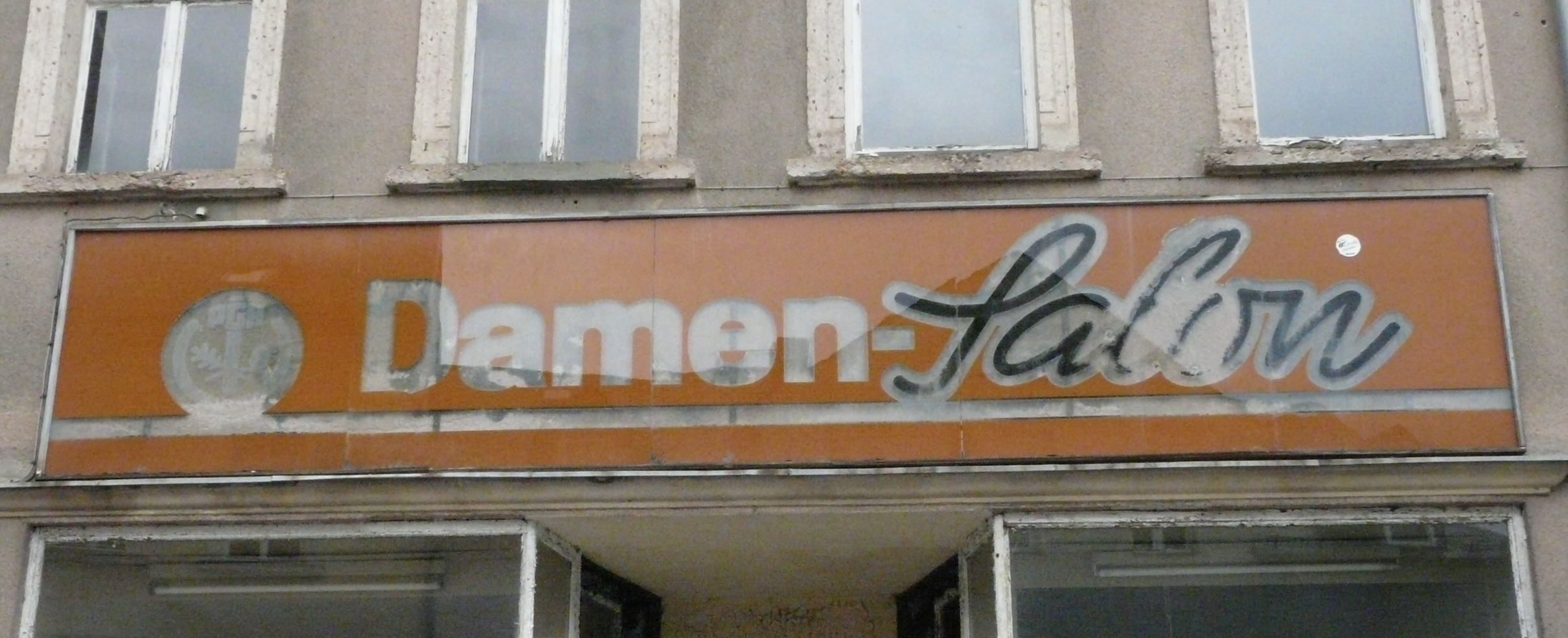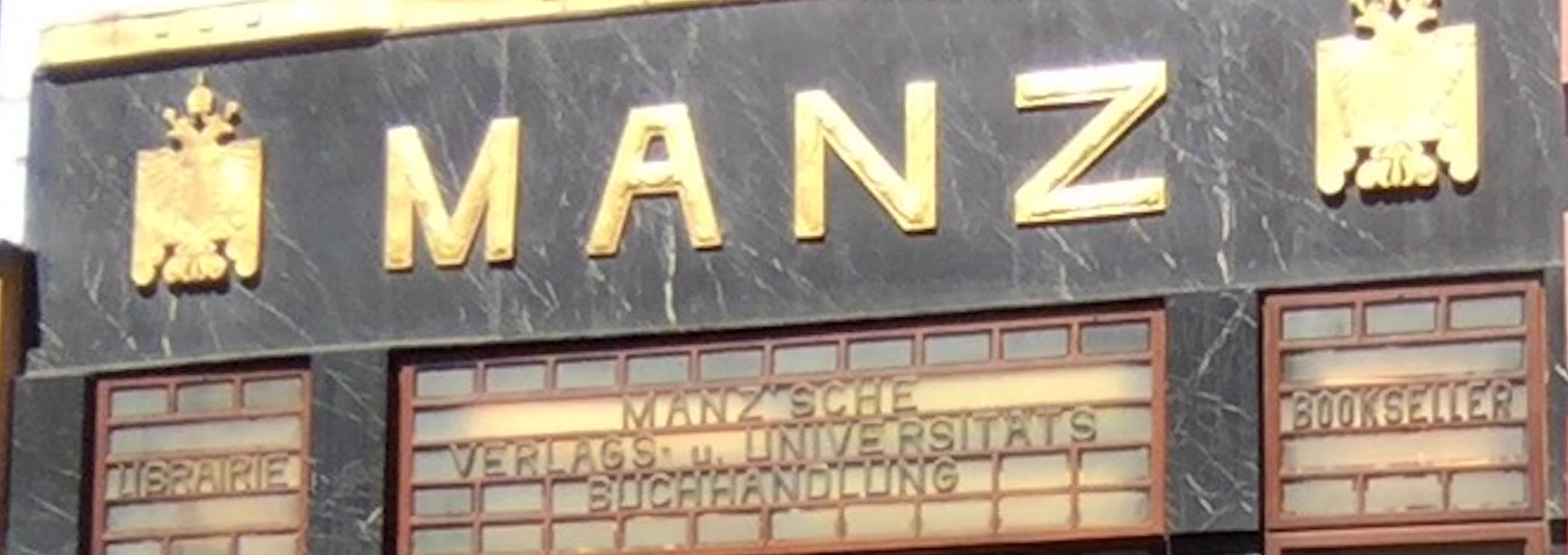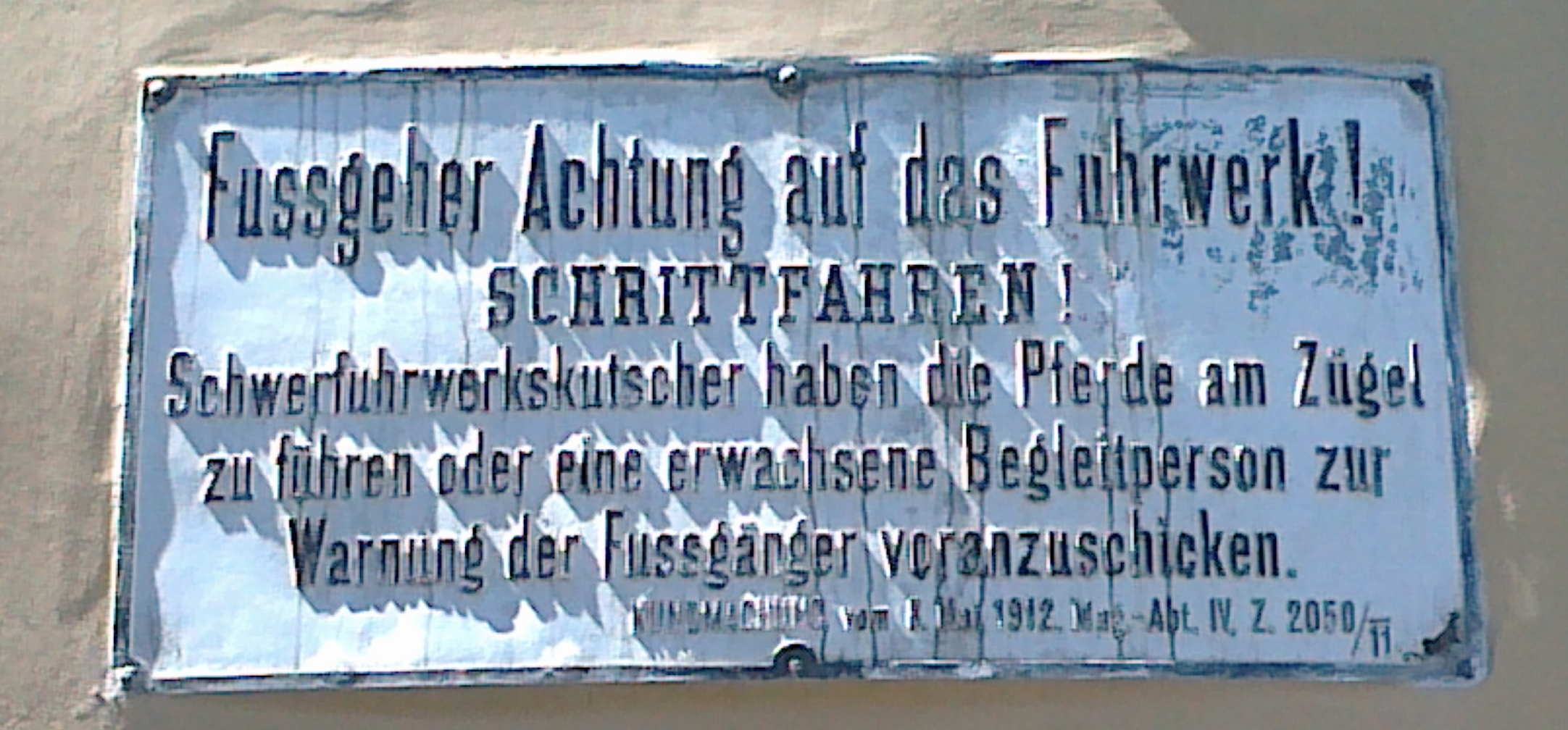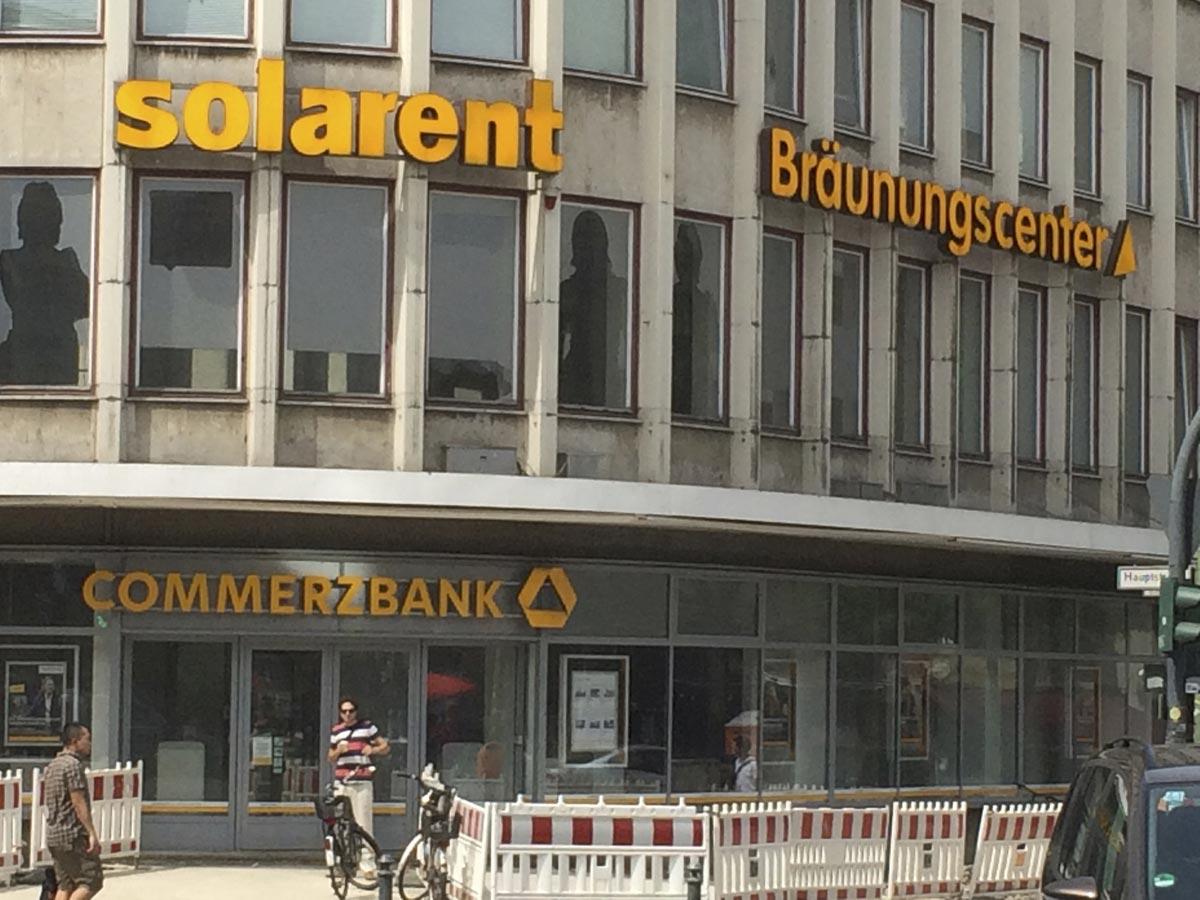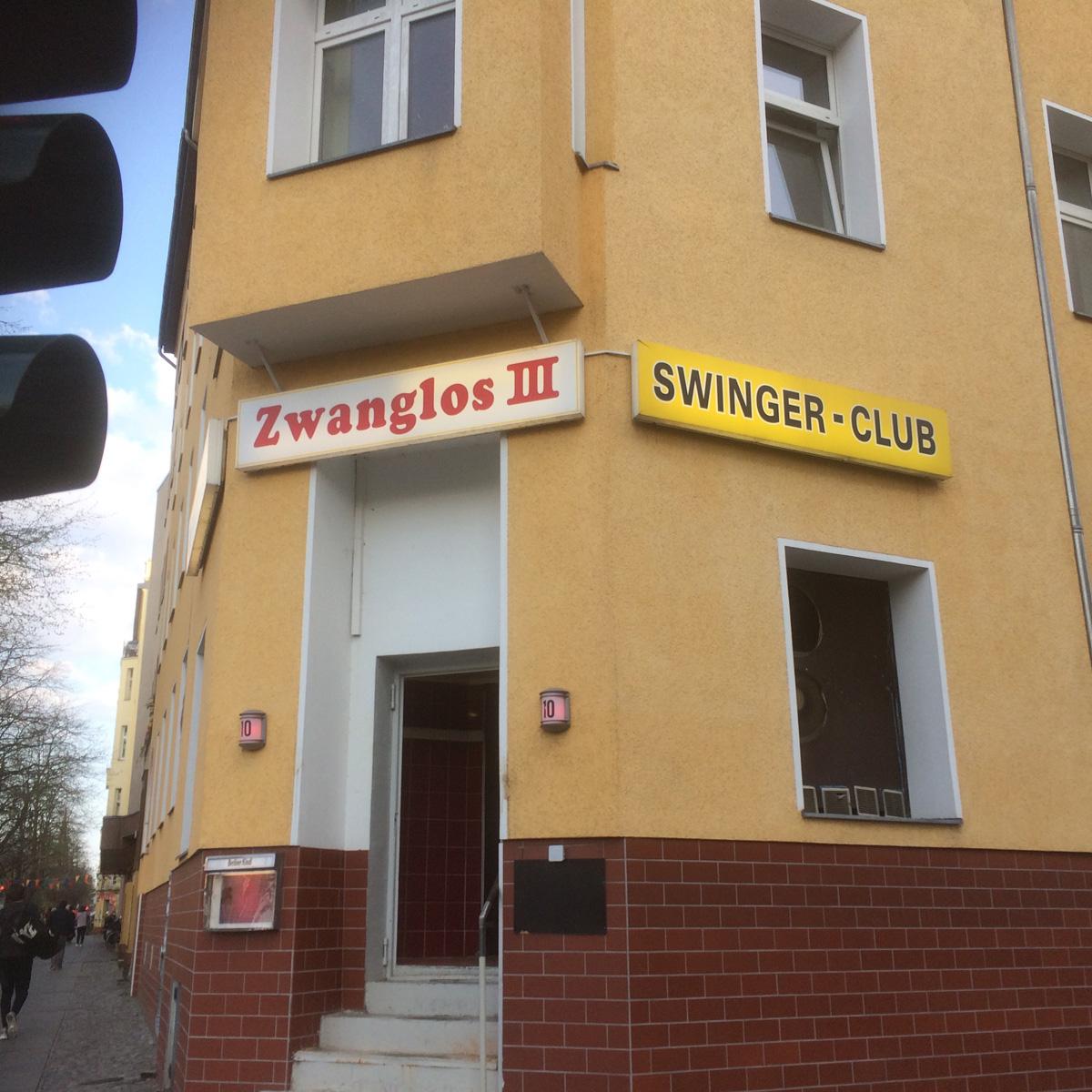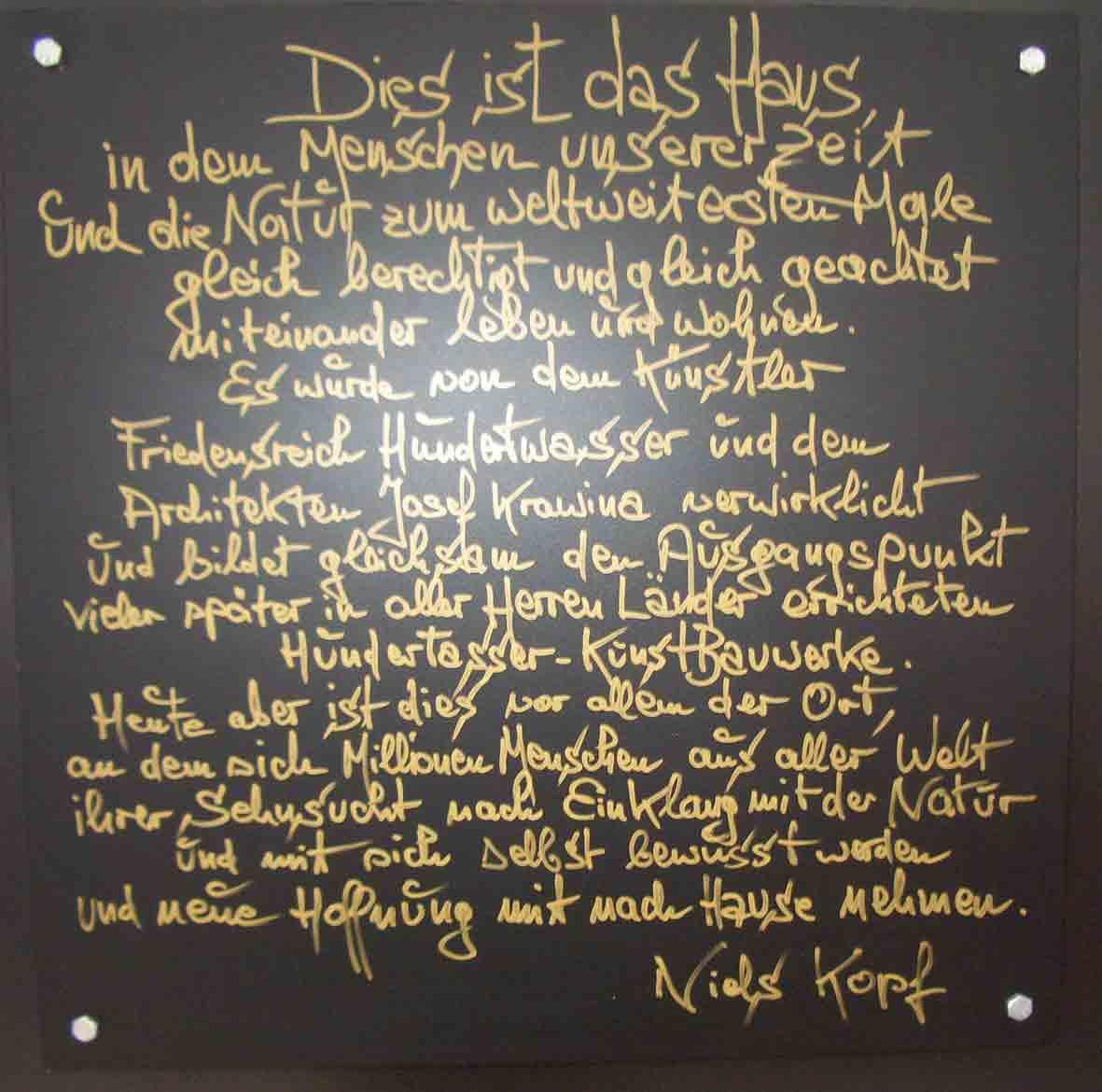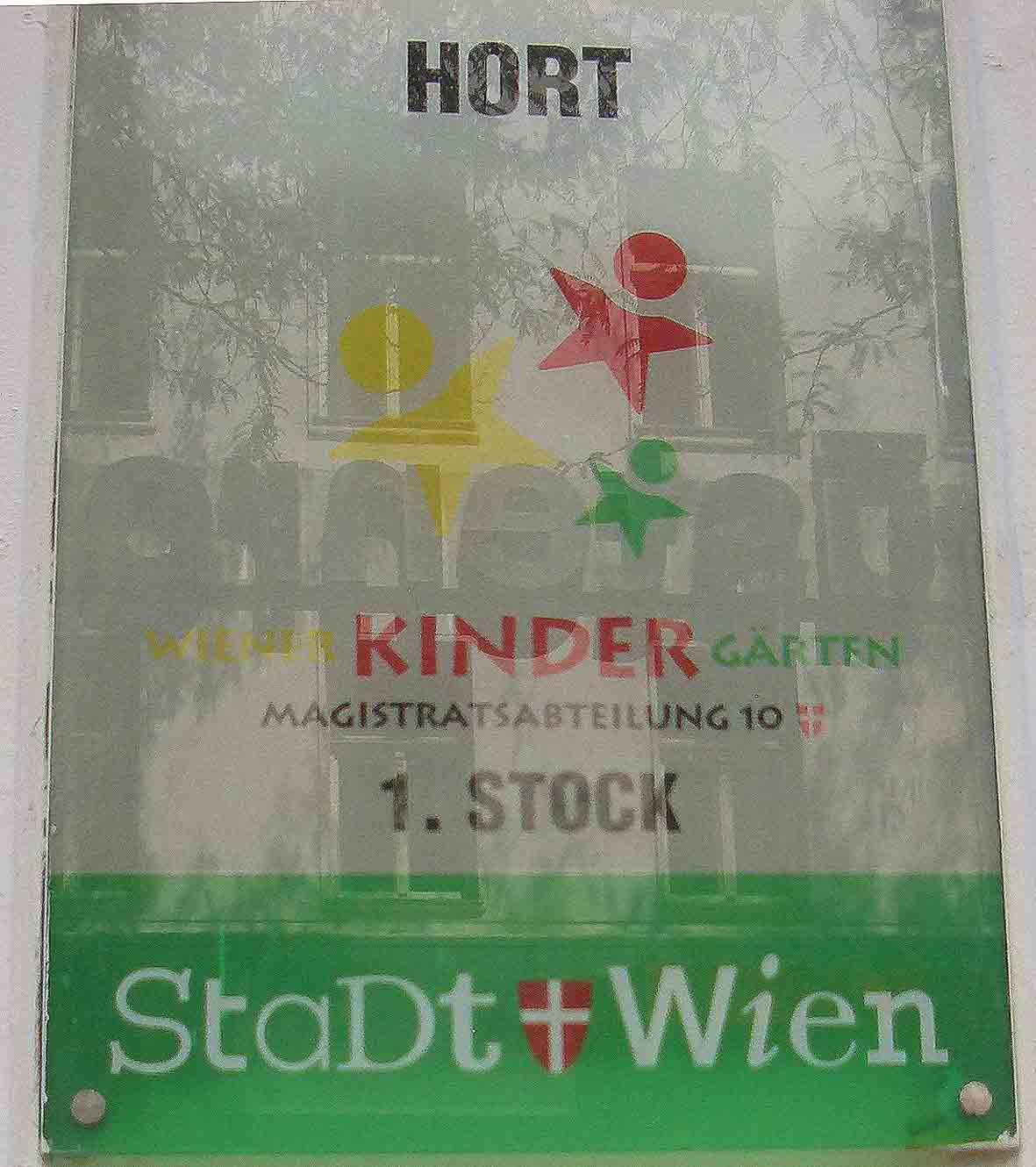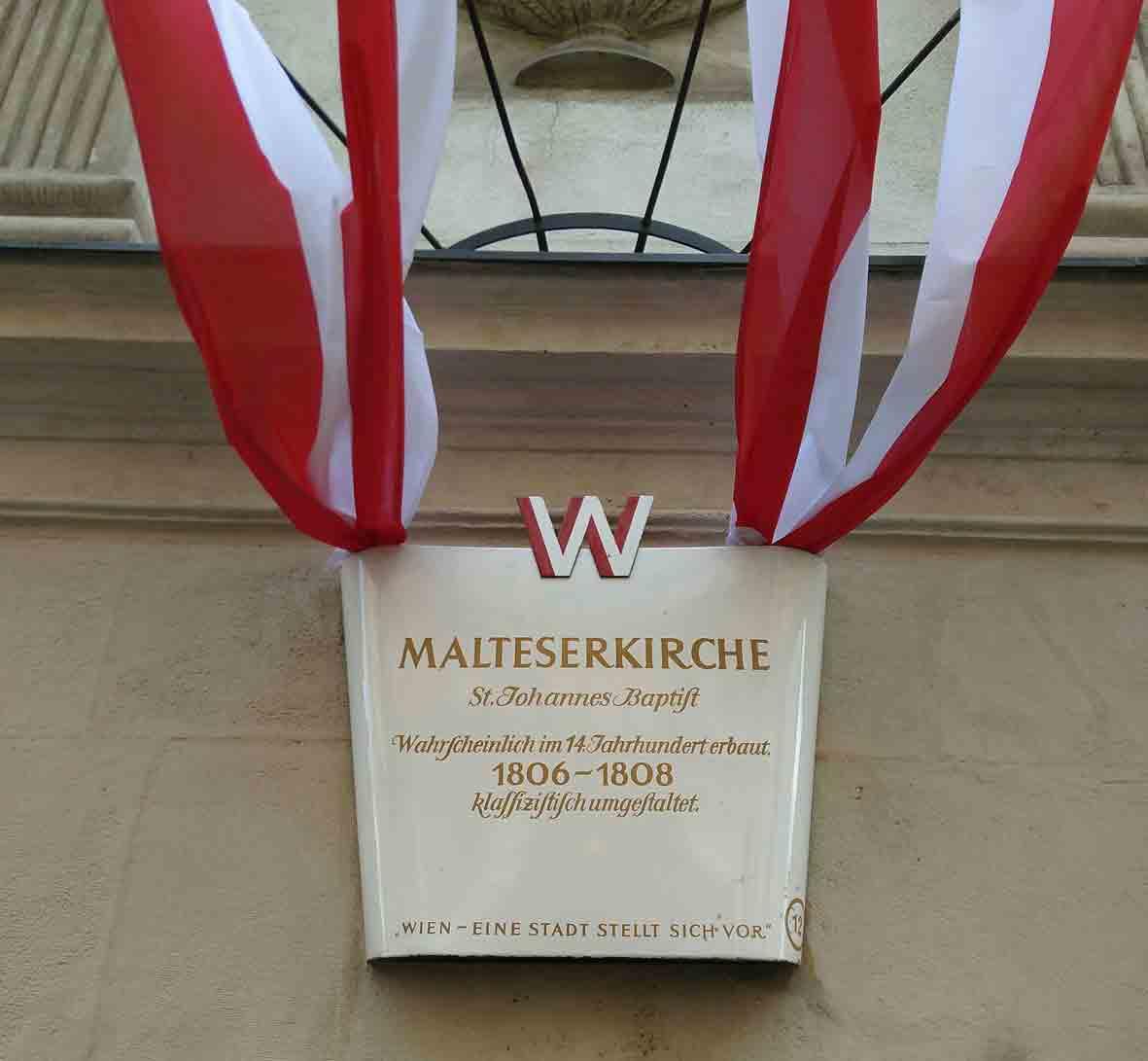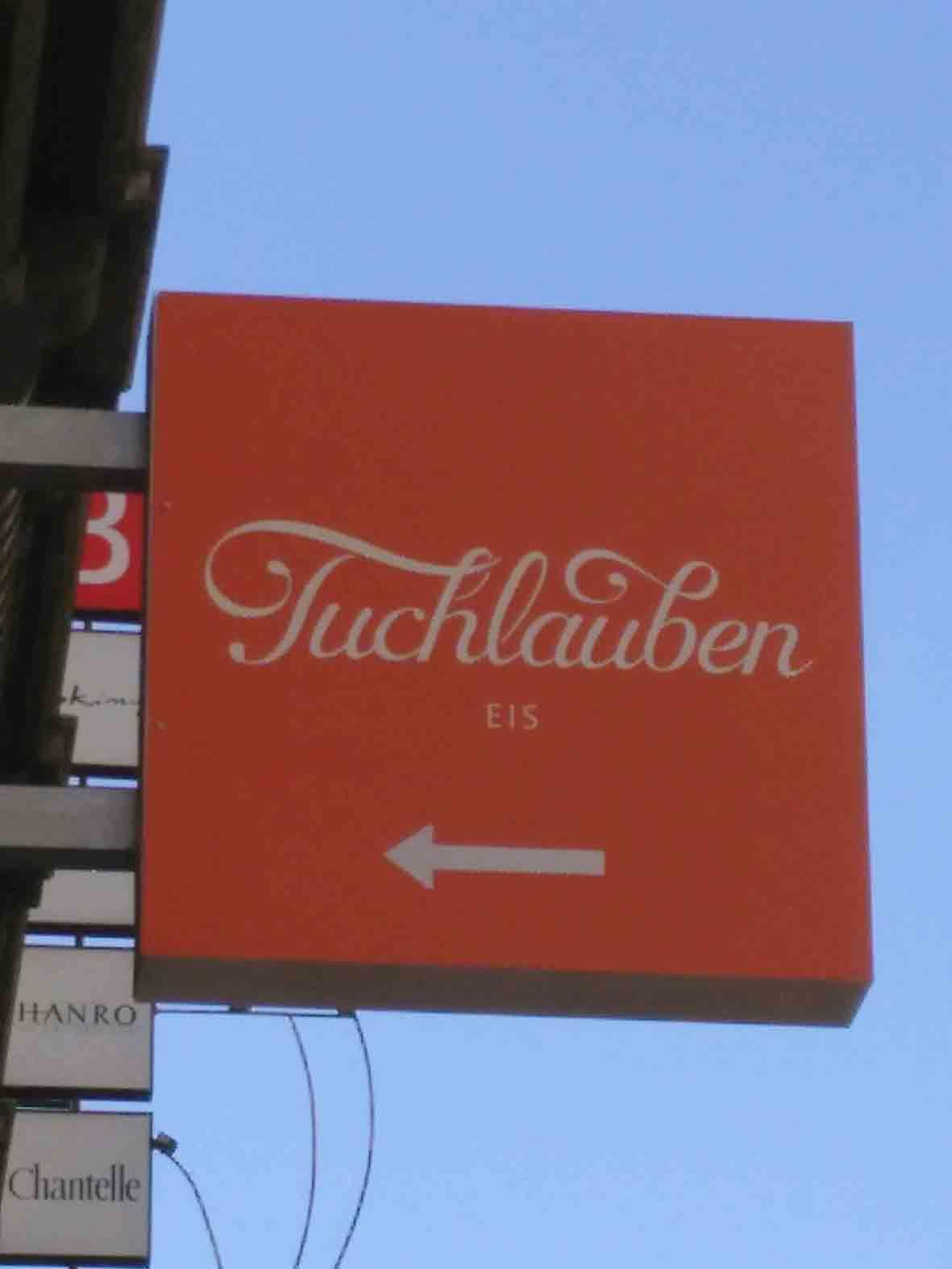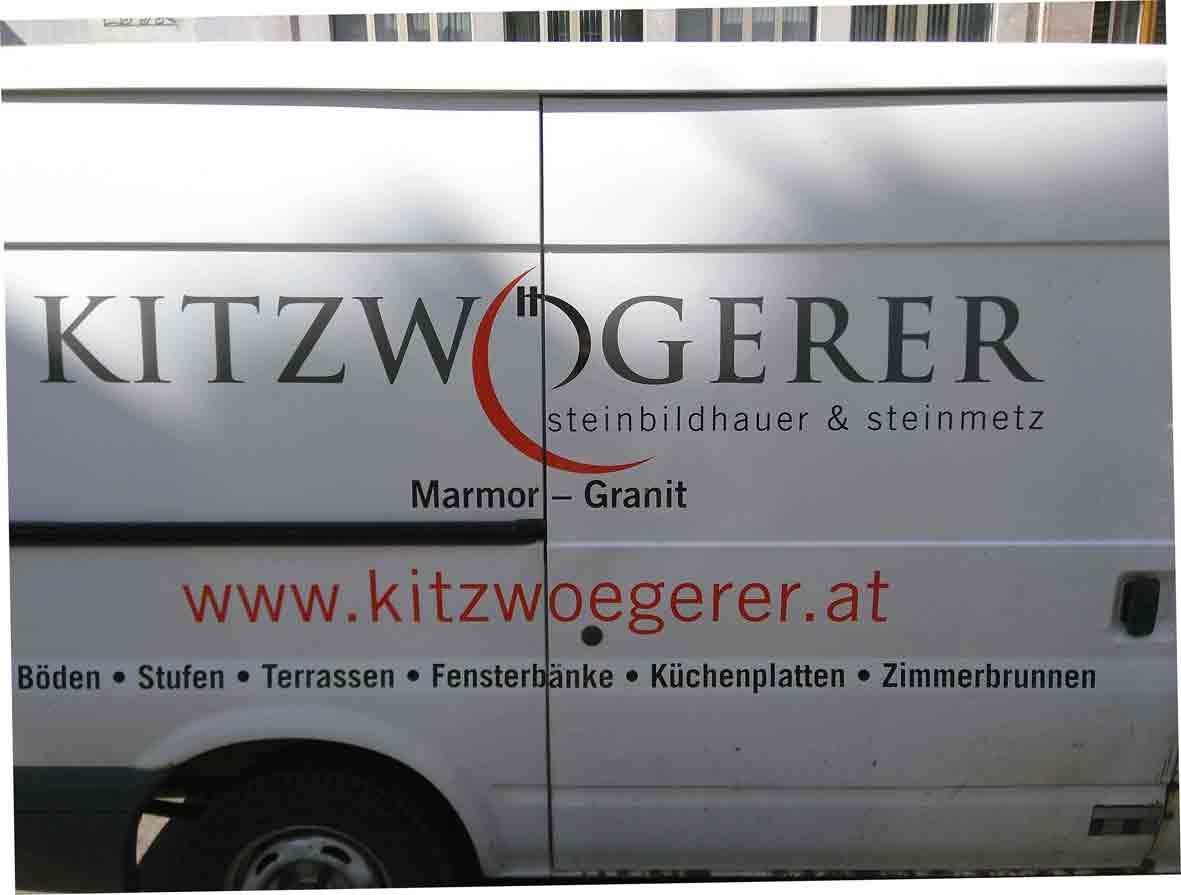
Typostreifzug durch die Stadt ...
5 Tage Côte d’Azur sind nun zu Ende und ich sitze wieder an der kalten Nordsee ...
Aber ich habe euch was mitgebracht:
In der Kathedrale von Grasse
Tourrette sur Loup
Mouans Sartoux
Hier ist jemand sehr aktiv mit der Schildermalerei. Alle gezeigten Bilder sind handgemalt und m. E. auch in einem Stil ...
Comic-Sans-Schildermalerei ... herrlich :mrgreen:
Cap Ferrat
Es gab noch so einen Brunnen, da war der Halbmond und das Kreuz noch eindeutiger herausgearbeitet. Leider war da aber mein Akku leer ...
Cagnes sur Mer – letzter Café vorm Rückflug
Der Schreiber hat wohl auch zu viel von dem Kaffee getrunken :shock:
Wien (War dämlich genug, die Akkus zwar aufzuladen, aber liegenzulassen, so daß ich in Wien ohne Kamera dastand und versucht habe, mit — für diesen Zweck völlig ungeeignetem — Funkfernsprecher und MacBook wenigstens ein paar Bilder dokumentarischer Qualität zu verfertigen. Und das, wo Wien so eine Kanaldeckelvielfalt hat. :cry:)5935cb75c1075_Bildschirmfoto2017-05-29um09_39_36.thumb.png.76d1cd5781c71149ad3d0c859d2f14b3.png
Deppenleerzeichen sind also keine Erfindung der Gegenwart.
Sohnemann ist derzeit gerade in einer extremen Eisenbahnphase. Wir waren daher im Eisenbahnmuseum in Didcot (in der Nähe von Oxford), wo hauptsächlich Stücke der Great Western Railway ausgestellt sind. Da waren ganz schicke Sachen dabei und auch beiden GWR-Logos fand ich hübsch!
das ist ja toll! Swing! Und wir können den Link zu den Eisenbahnbildern herstellen. Aber von III auf Gleis 29 ist es noch weit ...
Zwanglos „3“, Berlin Gneisenaustraße.
Oohh ja … darüber hab ich auch lange gegrübelt, ob das nicht doch eher zu den Typografischen Fundstücken passt, statt sowas hässliches hier zu posten. Also gerne weiter mit Musik (der arme Glenn Miller) …
PS: Weiter mit Musik, passt vielleicht besser …
"Mehr als 100 Jahre lächelten die Zipfelmützenmänner mit ihrer „Seifix“-Packung die Bewohner und Gäste des Stadtteils an."
Das stimmt aber doch nicht ganz. Ich kann mich noch gut daran erinnern, das auf den Grundstücken der Apotheke und dem Eckhaus ein anderes Haus stand, das wahrscheinlich schon kurz nach Anbringung der Zwergenwerbung dann schon in ca den 20er Jahren des letzten Jahrhunderts davor gebaut wurde. Dieses Haus hatte deutlich sichtbare Kriegsschäden und war nur recht einfach repariert gewesen, sodass es dann, ich glaube in den 1980er Jahren abgerissen wurde. Da tauchten dann die Zwerge in einer verwitterten, aber eigentlich schöneren Darstellung als die spätere Renovierung auf. Schade, dass es hiervon kein Foto gibt. Doff, dass ich das nicht selber gemacht habe.
Ein anderer Fall: In der Straße Schopenstehl, genau gegenüber der der Buceriusstraße wurde vor längerer Zeit ein Haus abgerissen, das seit etwa den 1950er Jahren dort stand. Dabei tauchten an den Hauswenden der älteren, aber noch etwas länger dort stehenden Gebäuden eine fast taufrische Wandbemalung rund um eine davor dort vorhandene Leuna-Tankstelle. Die Farben waren so frisch, dass man glauben konnte, sie seien grade erst an den Wänden angebracht. Kurze Zeit später wurden die Häuser mit der Reklame auch abgebrochen.
Ferner sind mir folgende Dinge ins Auge gefallen, die ich Euch nicht vorenthalten möchte:
Ein restaurierte Wandgemälde:
...das jetzt auch unter der Wandisolierung verschwunden ist :-(